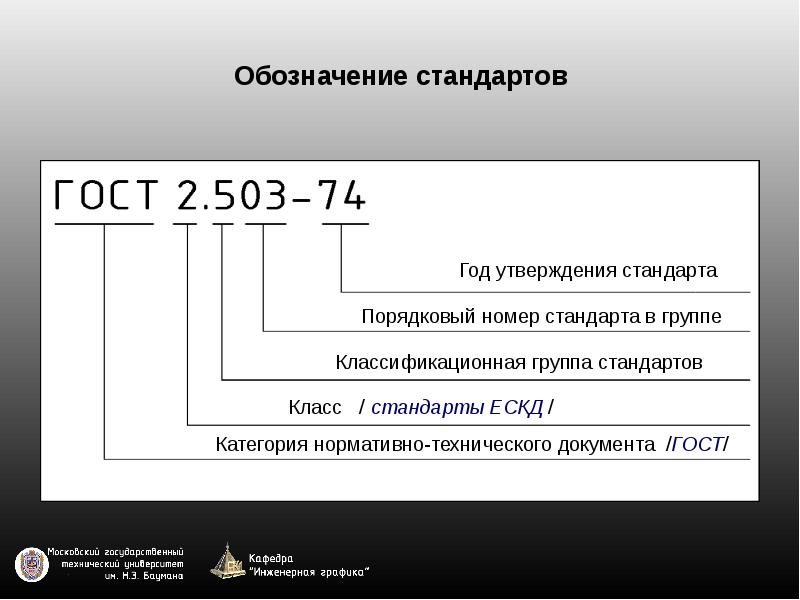
🗊 Презентация ЕСКД. Форматы, масштабы, линии, шрифты
Семинар 1 ЕСКД. Форматы, масштабы, линии, шрифты.
Единая система конструкторской документации - ЕСКД ЕСКД – комплекс стандартов, устанавливающих взаимосвязанные правила, требования и нормы по разработке, оформлению и обращению конструкторской документации, разрабатываемой и применяемой на всех стадиях жизненного цикла изделия (при проектировании, разработке, изготовлении, контроле, приемке, эксплуатации, ремонте, утилизации).
В системе 10 классификационных групп – от 0 до 9.
Обозначение стандартов
Форматы. ГОСТ 2.301- 68
Обозначение основных форматов: А0, А1, А2, А3, А4, А5
Масштабы. ГОСТ 2.302- 68 Масштаб – отношение линейного размера отрезка на чертеже к соответствующему линейному размеру того же отрезка в натуре.
Линии. ГОСТ 2.303- 68
Шрифты чертежные. ГОСТ 2.304- 81 d - толщина линий шрифта h – размер шрифта h = 1,8; 2,5; 3,5; 5; 7; 10; 14; 20; 28; 40 мм